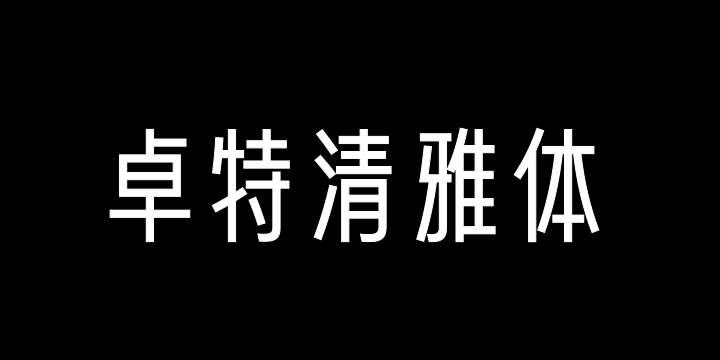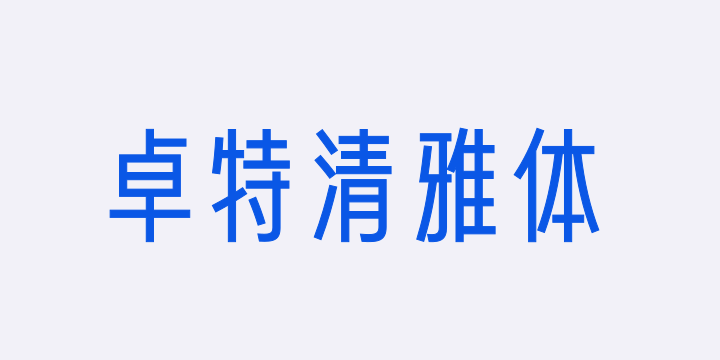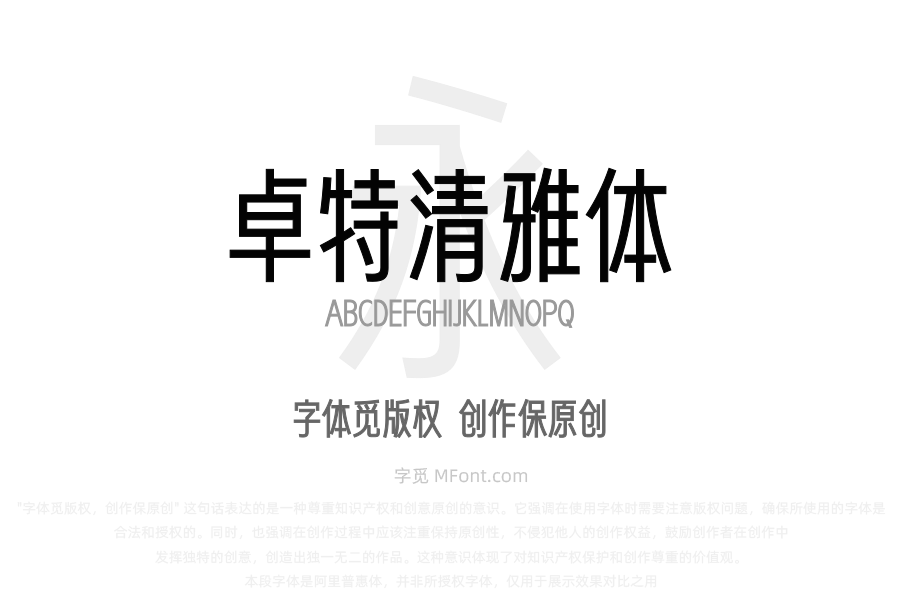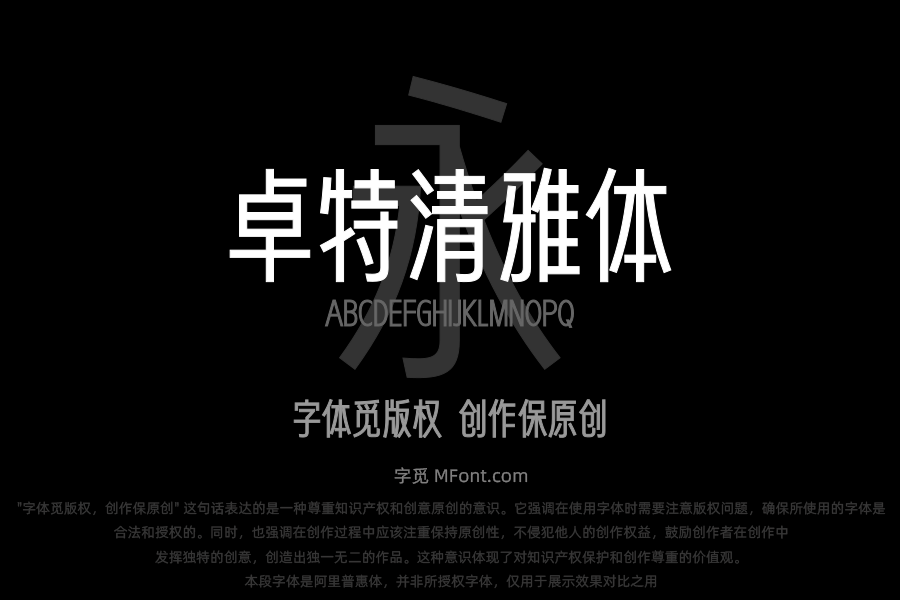
字体全名: 卓特清雅体
铸字厂: 卓特视觉字体
设计师: 山东兵克字库设计有限公司
字体简介: 卓特清雅体是一款由卓特视觉发布的开源简体中文字体,依据 SIL Open Font License 1.1(OFL)协议免费向公众开放使用。 本字体包含 GB2312-80 标准中的 6763 个简体汉字及 420 个常用字符,共收录 7183 个字符,可满足日常办公、设计创作、品牌宣传等多元场景的字体使用需求。